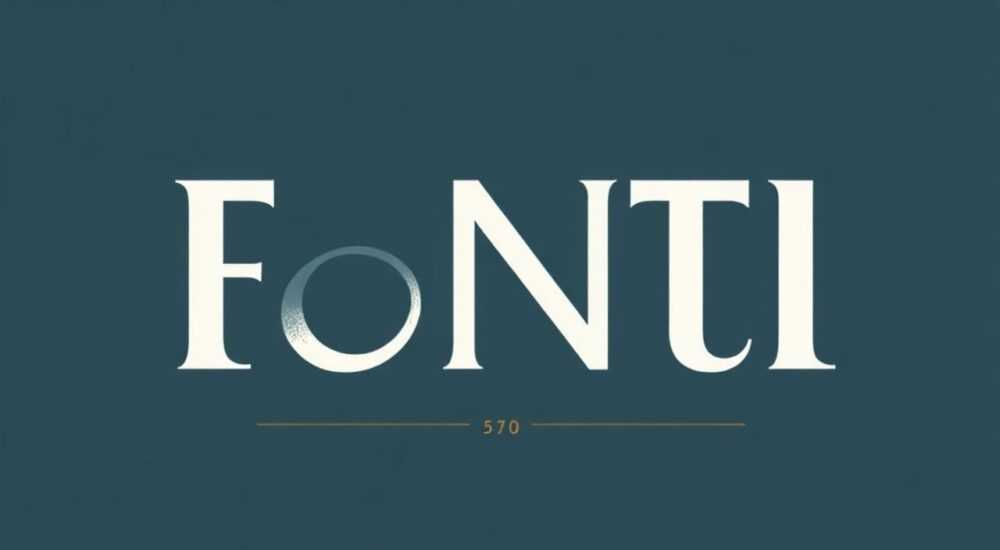
Как в фотошопе сделать красивый шрифт
В современной графическом дизайне шрифт — не просто средство передачи текста, а мощный инструмент эмоционального воздействия. Неправильно подобранный или плохо оформленный шрифт может разрушить даже самый впечатляющий визуальный композиционный замысел. В Adobe Photoshop, несмотря на его популярность как инструмента для ретуши и композитинга, скрыты мощные возможности для создания профессиональных, выразительных и визуально привлекательных шрифтов — от минималистичных логотипов до сложных типографских композиций. Многие дизайнеры ограничиваются стандартными настройками, не зная, как использовать слои стилей, маски, текстовые эффекты и ручное кернинг-выравнивание для достижения безупречного результата. В этой статье мы раскроем все тонкости: от базовых настроек до продвинутых техник, которые используют профессиональные типографы и креативные агентства по всему миру.
Почему шрифт решает всё: психология и визуальное восприятие
Шрифт — это не просто набор символов. Он несёт в себе эмоциональную нагрузку, культурный контекст и даже социальный статус. Исследования в области когнитивной психологии показывают, что люди оценивают надёжность бренда на 38% выше, если текст на его сайте или упаковке выдержан в стиле, соответствующем его сущности. Например, serif-шрифты (например, Times New Roman или Georgia) ассоциируются с традиционностью и авторитетом, а sans-serif (Helvetica, Futura) — с современностью и технологичностью. В Photoshop вы не просто редактируете текст — вы формируете восприятие.
Представьте, что вы создаёте афишу для премьеры классического спектакля. Использование жёсткого геометрического шрифта типа Impact вместо изящного Garamond сразу разрушит атмосферу. Даже если вы используете идеальную фотографию и цветовую палитру, неподходящий шрифт оттолкнёт целевую аудиторию. Именно поэтому в профессиональной типографике шрифт выбирают первым — до цвета, до макета.
Как выбрать правильный шрифт для вашего проекта
Выбор шрифта — это не вопрос личного вкуса, а стратегическое решение. Начните с анализа цели: реклама, логотип, плакат, цифровой баннер? Каждый тип проекта требует своего подхода.
Для логотипов подойдут уникальные или модифицированные шрифты — например, Montserrat, Raleway или Oswald. Они хорошо масштабируются и легко адаптируются под графические изменения. Для длинного текста — только читаемые шрифты: Lora, Open Sans, PT Serif. Избегайте декоративных шрифтов в блоках с более чем 30 словами — они утомляют глаз.
Используйте инструмент «Палитра шрифтов» (Window > Character) для предварительного просмотра. Выделите текст, кликните по стрелке рядом с именем шрифта — и вы увидите живой превью всех доступных вариантов. Это экономит часы проб и ошибок.
Базовые настройки текста: кернинг, трекинг, выравнивание
Кернинг — это расстояние между двумя конкретными буквами. Трекинг — это равномерное изменение расстояния между всеми символами в тексте. Эти два параметра часто путают, но их правильное применение делает разницу между «нормальным» и «профессиональным» текстом.
Для кернинга выделите пару букв (например, «AV» или «To») и используйте клавиши Alt + ← / → (Windows) или Option + ← / → (Mac). В Photoshop по умолчанию стоит «Автоматический кернинг», но он часто ошибается. Особенно критично это для заголовков — там даже 5–10 единиц могут улучшить восприятие.
Трекинг применяйте для всего текста, если он кажется слишком плотным или разреженным. Для заголовков — от -20 до +50. Для абзацев — от -10 до +15. Не превышайте +50 — текст станет нечитаемым.
Выравнивание — ещё один ключевой момент. Не используйте «Выравнивание по левому краю» для центрированных заголовков. Если текст короткий — центрируйте. Если длинный — выравнивайте по левому краю, но не «по ширине»: это создаёт неравномерные пробелы между словами, что разрушает ритм чтения.
Слои стилей: создание объёма и глубины
Слои стилей — главный инструмент в Photoshop для превращения обычного текста в визуально насыщенный элемент. Откройте панель «Стили слоя» (Layer > Layer Style) и начните с базовых эффектов.
Начните с внешней тени — она создаёт ощущение глубины. Угол 120°, расстояние 4–6 пикселей, размытие 6–10 — идеальный баланс. Не используйте черную тень — выбирайте серый (#333333) или цвет, соответствующий фону.
Внутренняя тень придаёт тексту «вырезанность». Используйте её с осторожностью: прозрачность 30–40%, размер 3–5 пикселей. Хорошо работает на градиентных фонах.
Обводка — мощный инструмент для выделения текста на сложном фоне. Толщина 1–2 пикселя, цвет контрастный, но не яркий. Белая обводка на тёмном фоне — классика. Чёрная на светлом — рискованно, может «залипнуть».